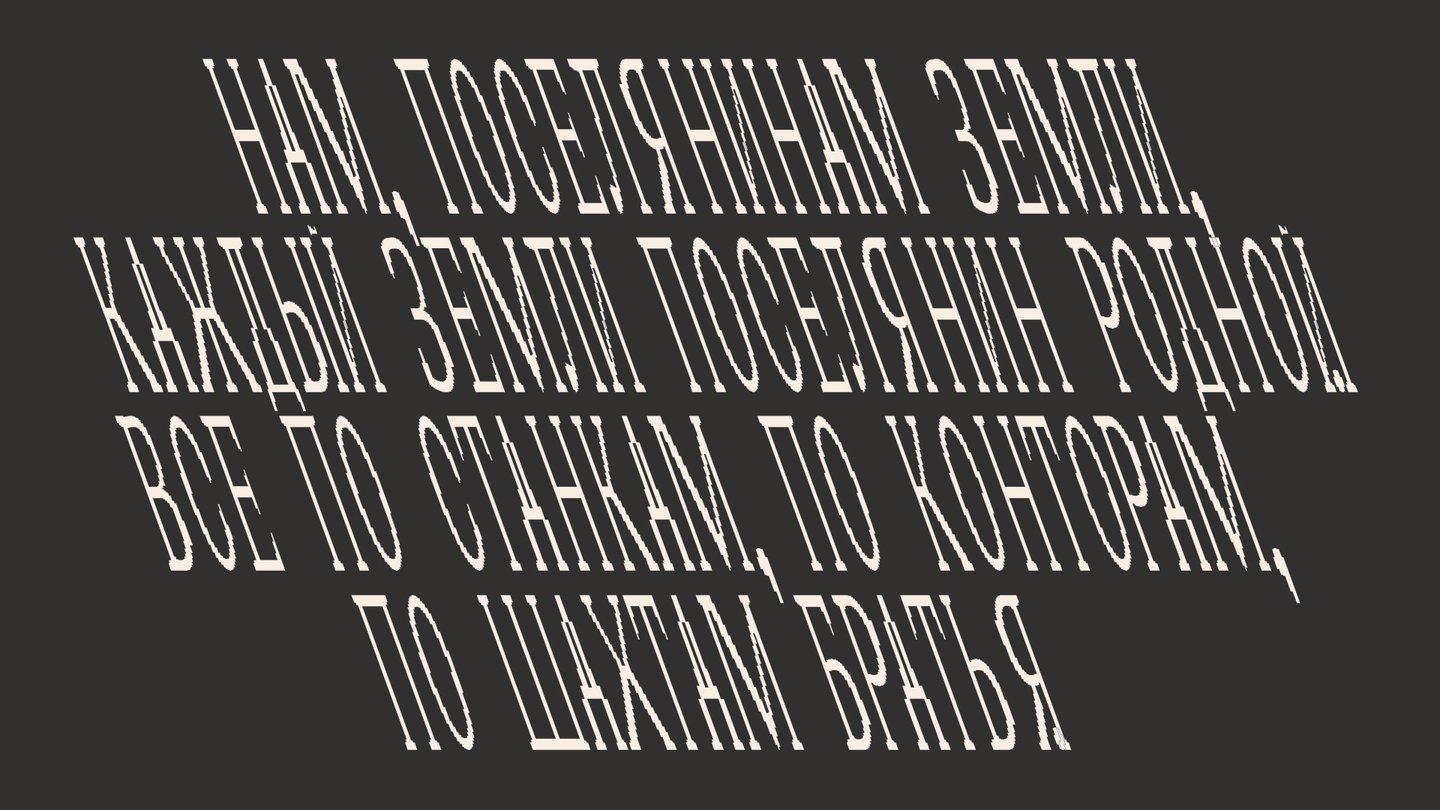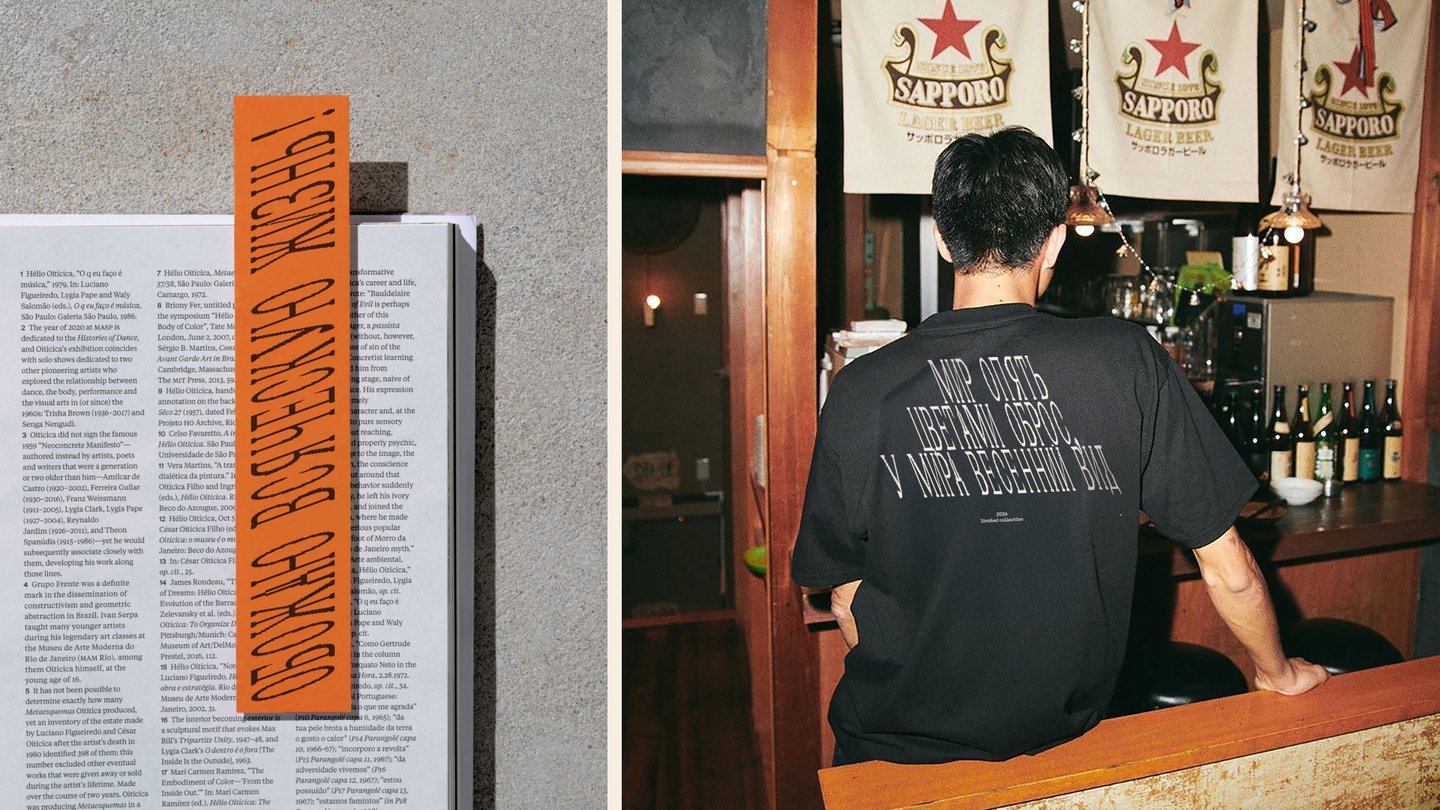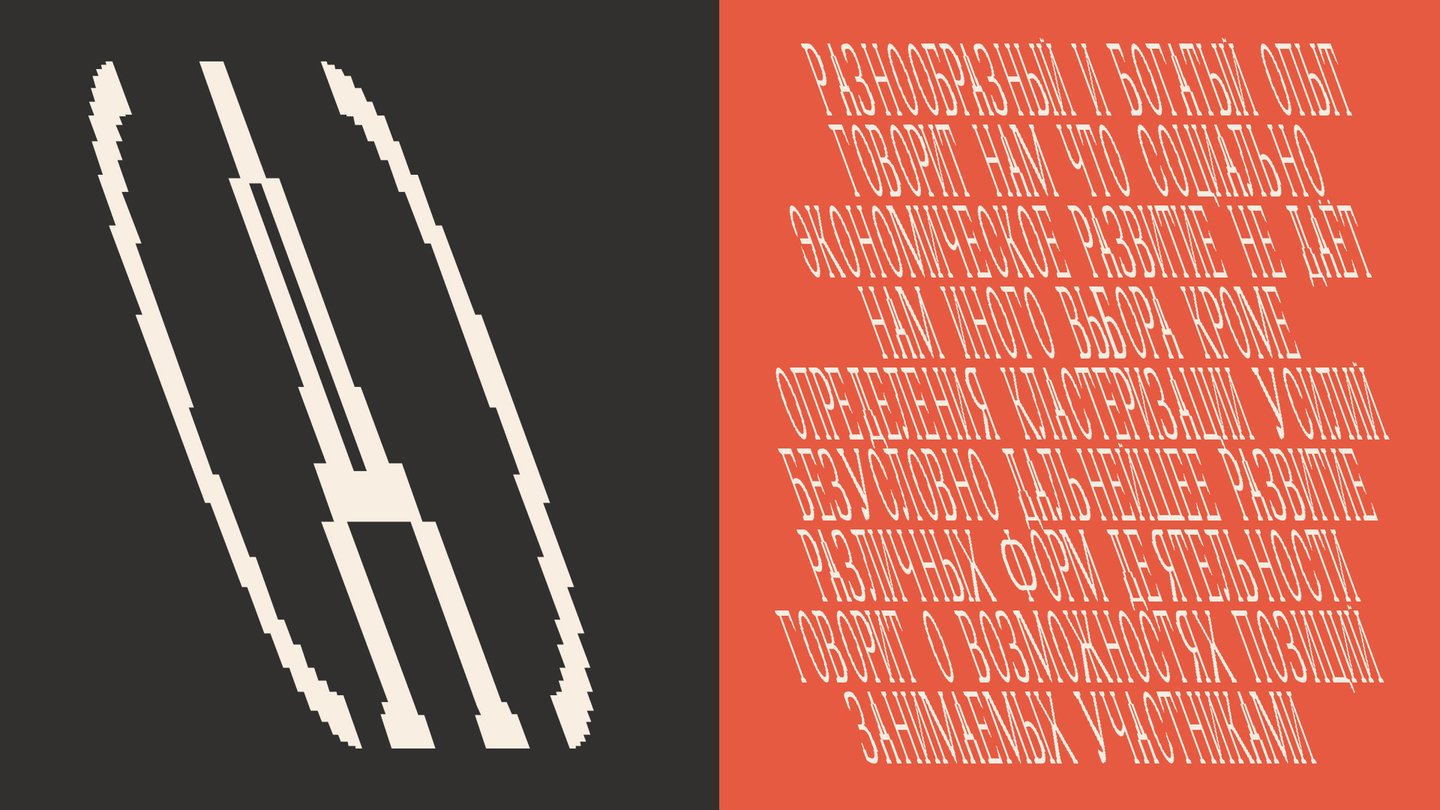
Основа — контрастная антиква с резаными засечками. Контур каждой буквы вибрирует, крошится, теряет ровный край, будто текст пропустили через плохой ксерокс. В этом заключается двойное движение. С одной стороны — родословная строгого книжного шрифта, дисциплинированная геометрия, узкий кегль, подходящий для длинных высказываний. С другой — фактура тревоги: дрожь, эрозия, ощущение текста-крика, текста-транспаранта. Шрифт одинаково уместен и в спокойном заголовке художественного каталога, где достаточно намёка на неровность, чтобы читатель насторожился, и в плакате, где буквы валятся друг на друга по диагонали, как строчки манифеста.